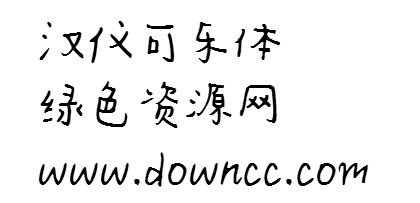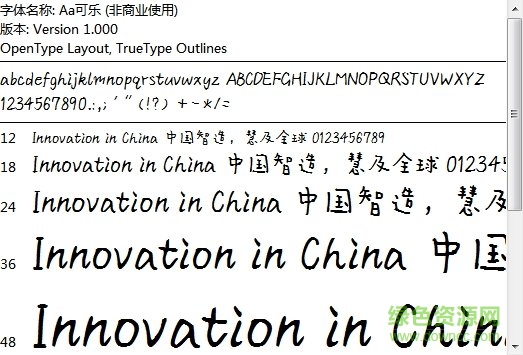
漢儀可樂體是一款字跡干爽、清晰醒目的中文字體,采用了手寫體的設(shè)計(jì)風(fēng)格,文字更顯端正簡潔,喜歡的朋友可以來綠色資源網(wǎng)下載吧!
可樂體,是安卓字體大師推出的一款手機(jī)字體,文風(fēng)干凈字跡干凈,能給人很大的好感度,讓你的藝術(shù)設(shè)計(jì)更有獨(dú)特韻味。
漢儀可樂體由漢儀字體推出的一款手寫字體,并不是常見標(biāo)志上的藝術(shù)字體,字跡更加娟秀精簡,便于大家的閱讀和辨認(rèn),運(yùn)用在藝術(shù)設(shè)計(jì)上都很有效。